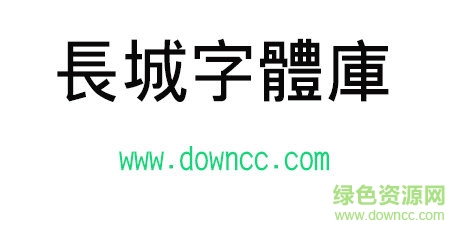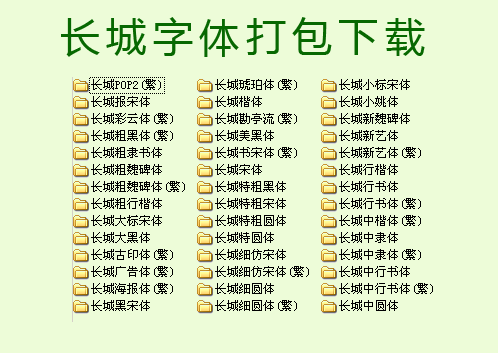
長(zhǎng)城字體是電腦中非常常見(jiàn)的一種字體類(lèi)型,其應(yīng)用的范圍也非常廣泛,通常在書(shū)法家的作品、平面廣告詞設(shè)計(jì)和特殊的書(shū)籍上面都有這種字體,也是非常的實(shí)用,需要的朋友可別錯(cuò)過(guò)了,歡迎來(lái)綠色資源網(wǎng)下載使用哦。
此次發(fā)布的這個(gè)“長(zhǎng)城字體庫(kù)”,一共包含了42款精美的長(zhǎng)城字體,都是精品。。